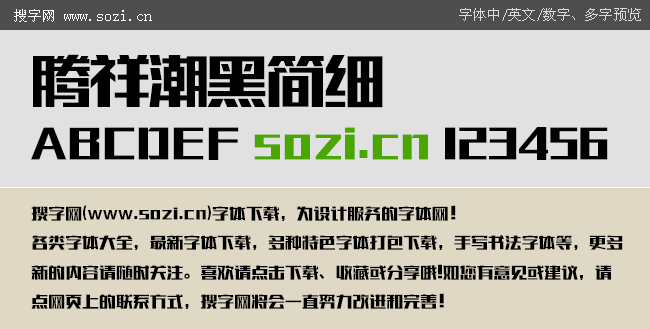
騰祥潮黑簡細(xì)
搜字網(wǎng)提供一款騰祥潮黑簡細(xì)中文藝術(shù)字體下載,騰祥潮黑簡細(xì)是在潮黑基礎(chǔ)上減細(xì)設(shè)計(jì)而成,字形結(jié)構(gòu)扁方、端莊,橫豎筆畫粗細(xì)比例適度、豎筆粗壯有力,布白均勻、行文貫通,并且部分點(diǎn)和提、撇和點(diǎn)做連筆畫處理,更好的展現(xiàn)出字形的連貫性和整體感。騰祥潮黑簡細(xì)筆畫簡潔有力細(xì)微處變換靈動,即實(shí)用又富有裝飾效果,能夠適合標(biāo)題和屏顯用字,可用于印刷出版、包裝設(shè)計(jì)、廣告設(shè)計(jì)、網(wǎng)頁設(shè)計(jì)、屏幕顯示等。